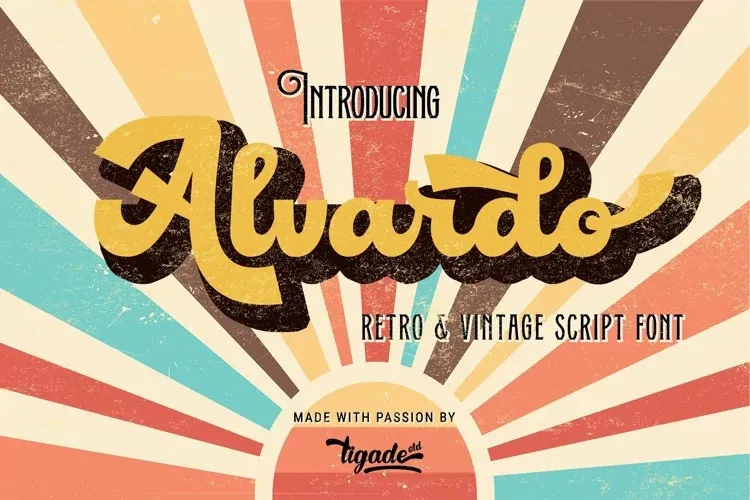
A fonte ‘Alvardo’ é uma paleta elegante e vintage com traços cursivos, criada pelo designer Tigade Std. Esta cufa foi projetada para oferecer fácil acesso a todos os gílios e alternativas estilísticas, tornando-a perfeita para um uso em variedades de formatos gráficos, incluindo produtos, headlines de revistas, logos, materiais promocionais e embalagens. Suas linhas suaves e sutis enriquecem qualquer projeto, trazendo uma sensação nostálgica ao design contemporâneo. Utilizando ‘Alvardo’, você pode revitalizar suas criações, dando-lhes um toque antigo que se sobressai em qualquer layout visual. Seja para o seu próximo projeto de design gráfico ou marketing digital, ‘Alvardo’ é uma escolha irresistível.